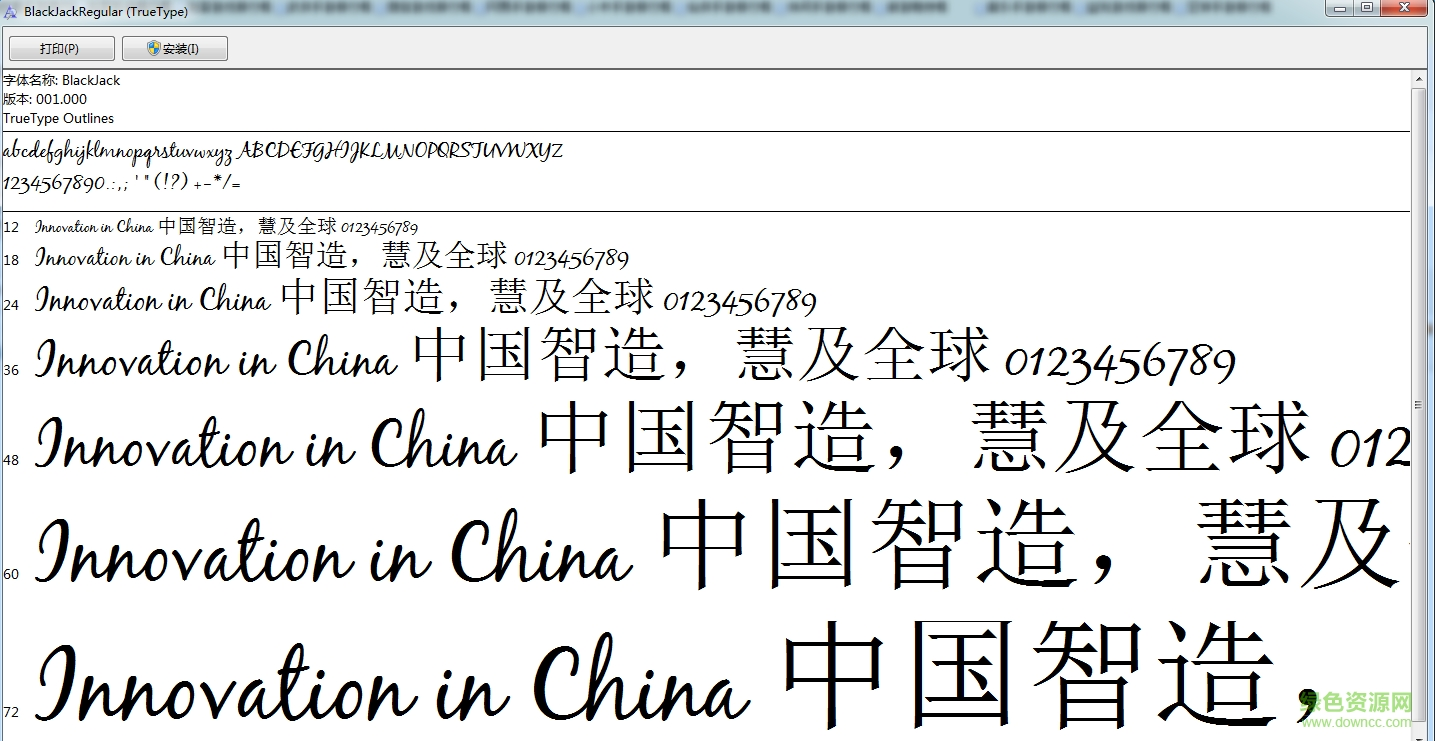
blackjack字體是一款好看的英文字體,字型比較隨意,比一般電腦設(shè)計(jì)出來(lái)的無(wú)襯線字體更加生動(dòng)有趣,喜歡該字體的小伙伴快來(lái)綠色資源網(wǎng)下載吧!
blackjack字體可以運(yùn)用到比較廣泛的區(qū)域,例如名片設(shè)計(jì)、美工設(shè)計(jì)、海報(bào)廣告、新聞媒體、宣傳海報(bào)、ppt、影視制作以及任何使用文字的領(lǐng)域。
blackjack字體是手寫字體,筆畫連綿,字形花哨,整個(gè)書寫看著比較有曲線,非常引人注目,常常用于黑板書寫設(shè)計(jì)方面!